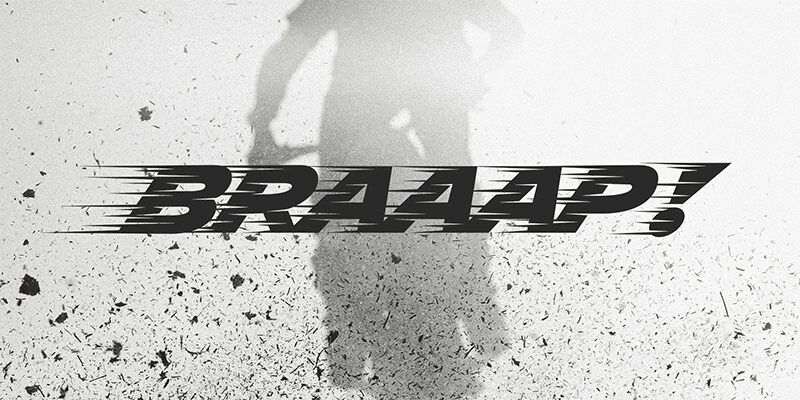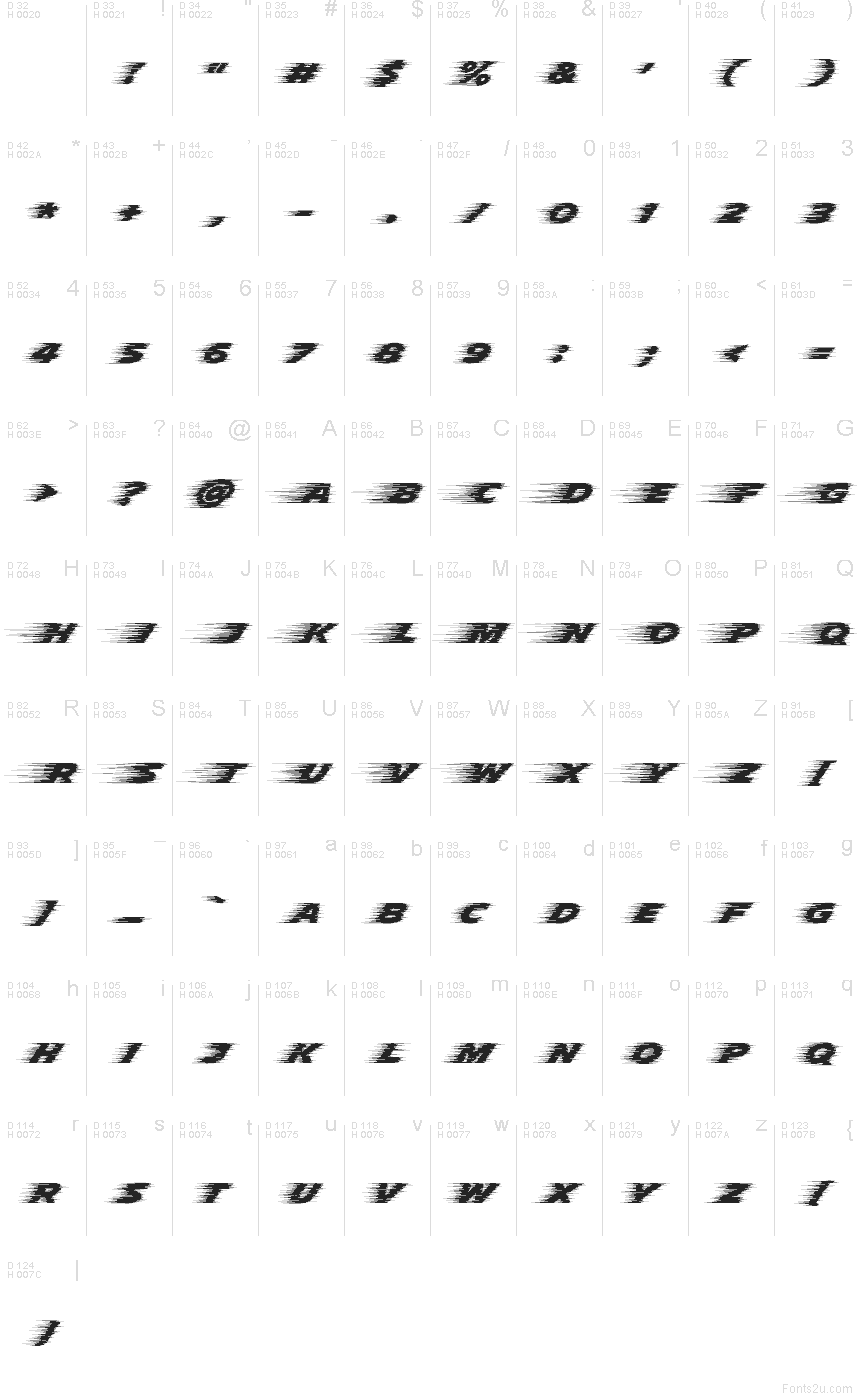
Braaap-S11
Braaap-S11 od Youssef Habchi je bezplatné písmo typu display s rýchlym, pretekárskym štýlom. Písmená sú pretínané dlhými horizontálnymi rezmi a drsnými šikmými ťahmi, čo celej sade dodáva efekt pohybového rozostrenia a vysokej rýchlosti bez toho, aby stratila svoje základné tvary.
Braaap-S11 skvele funguje na plagátoch motoristických športov, grafike so stunt tematikou, názvoch hier, akčných logách, letákoch na podujatia a výrazných prvkoch, kde má byť rýchlosť jasná na prvý pohľad. Toto bezplatné písmo sa hodí aj na športový branding, agresívne citáty alebo krátke nadpisy, pretože narušená textúra prenáša pocit pohybu do každého slova.